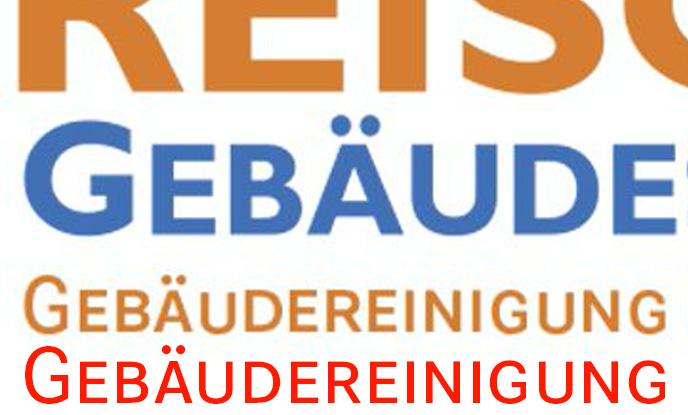
Suche Hausschrift einer Gebäudereinigungsfirma
kennt jemand die Schriftart der Beispielgrafik im Anhang? Die Auflösung ist leider nicht so der Hit.
Es handelt sich hierbei um die Hausschrift einer Gebäudereinigungsfirma in Bayern.
Der Font ist wohl einmal Bold und einmal Regular...
Welche Reinigung ist’s denn?
Bei dem G scheint mir die Roboto eine mögliche Kandidatin.
Beim ersten G und den Ä-Punkten hätte ich jetzt die Corporate S vermutet …
Bei der Schriftart wurde wohl manuell der erste Buchstabe immer größer gemacht oder?